D y E construidas en Cinema 4D como volúmenes de bronce envejecido. La geometría — fusión de esferas de radio variable sin aristas — no remite a ningún alfabeto conocido: libre de convenciones caligráficas o constructivas, la identidad de los objetos es exclusivamente material.
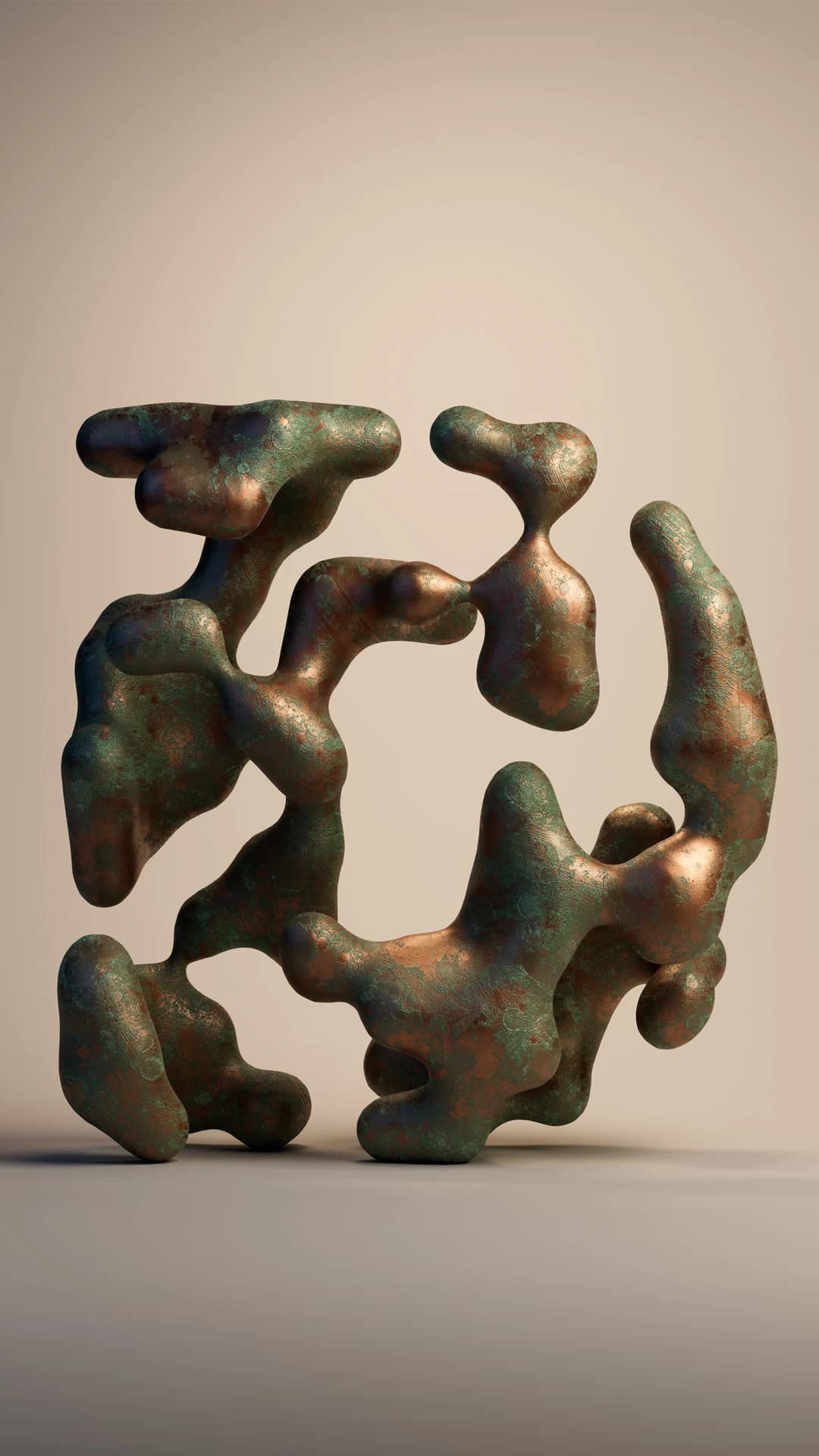
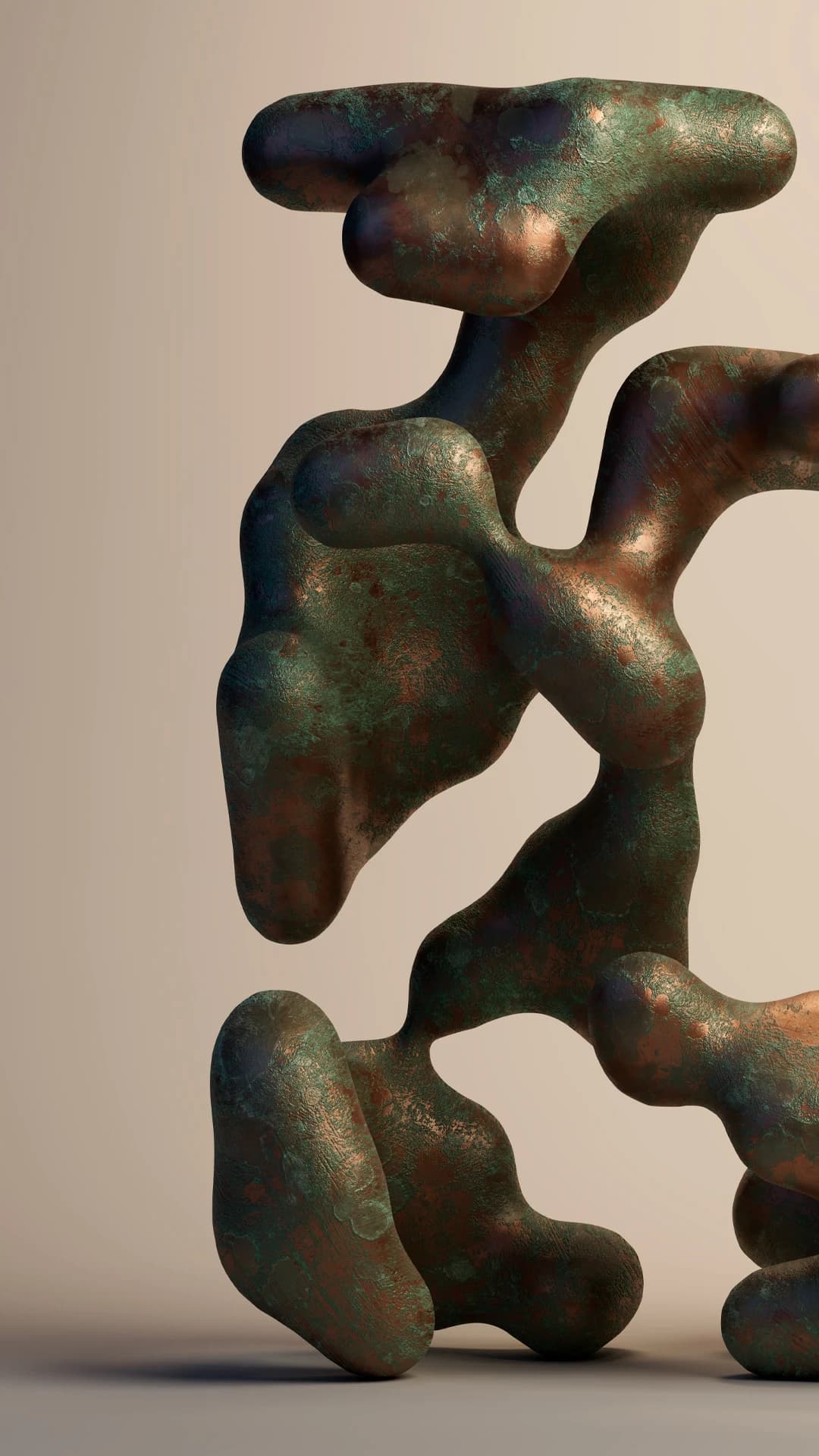
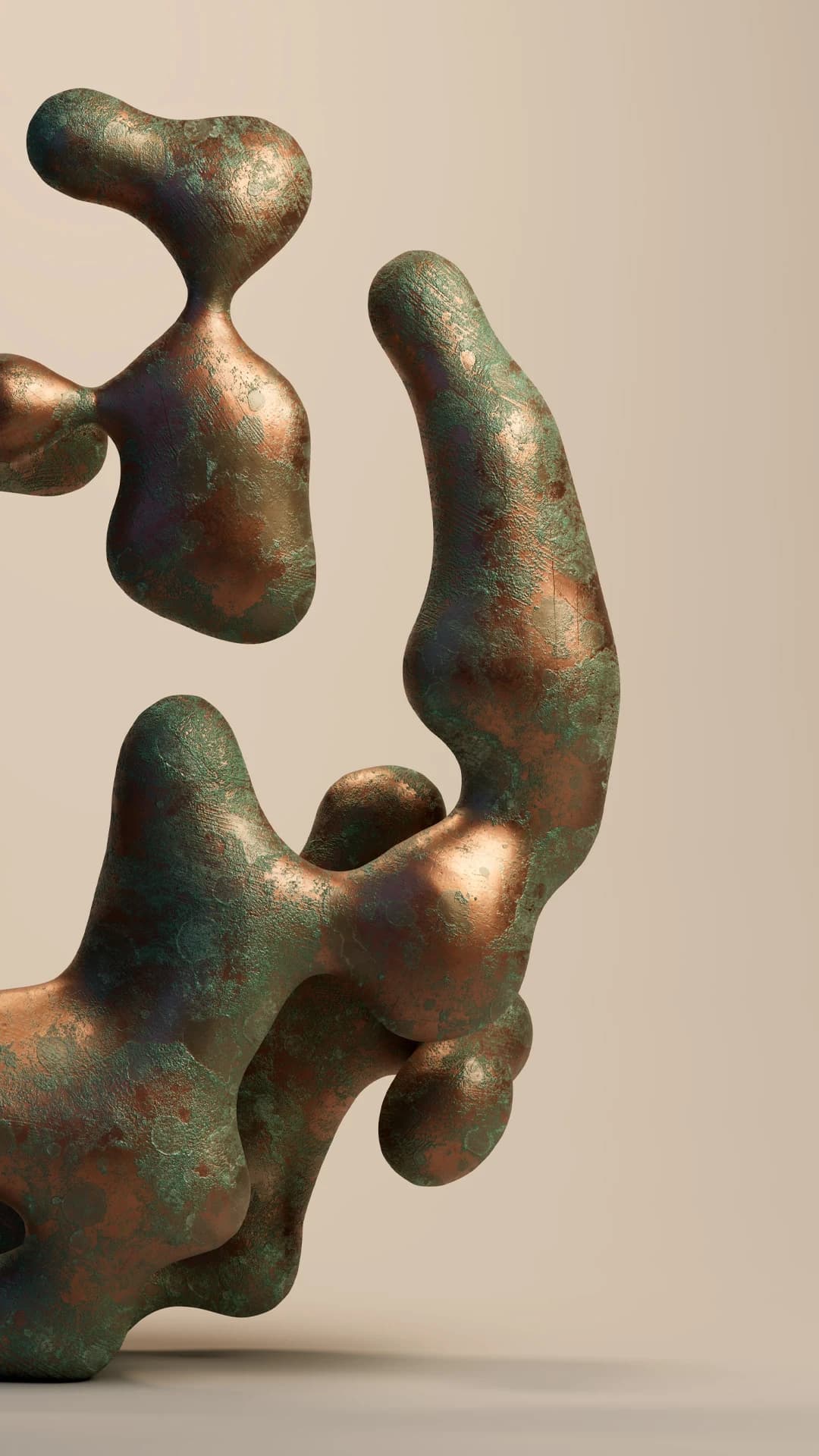
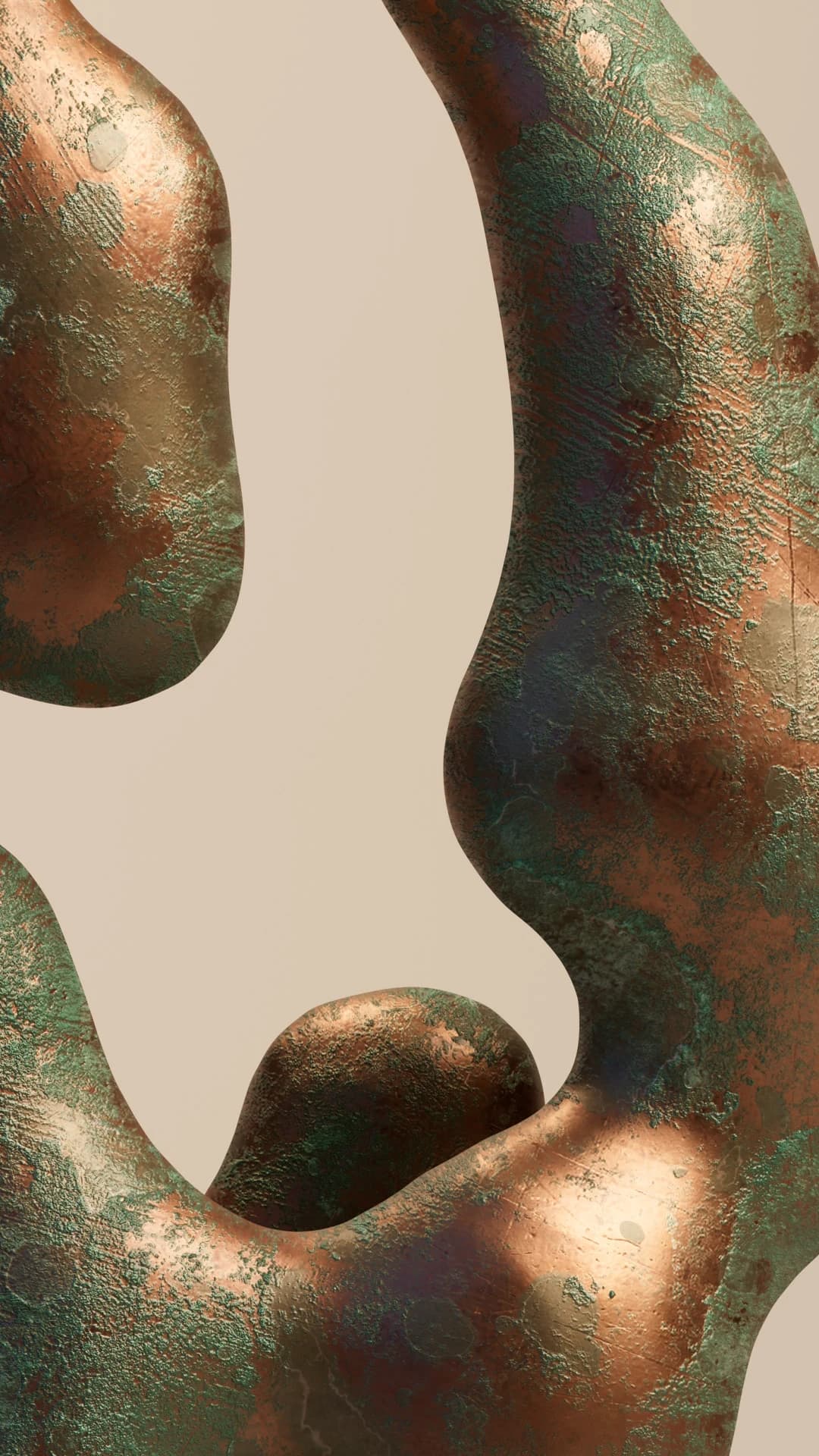
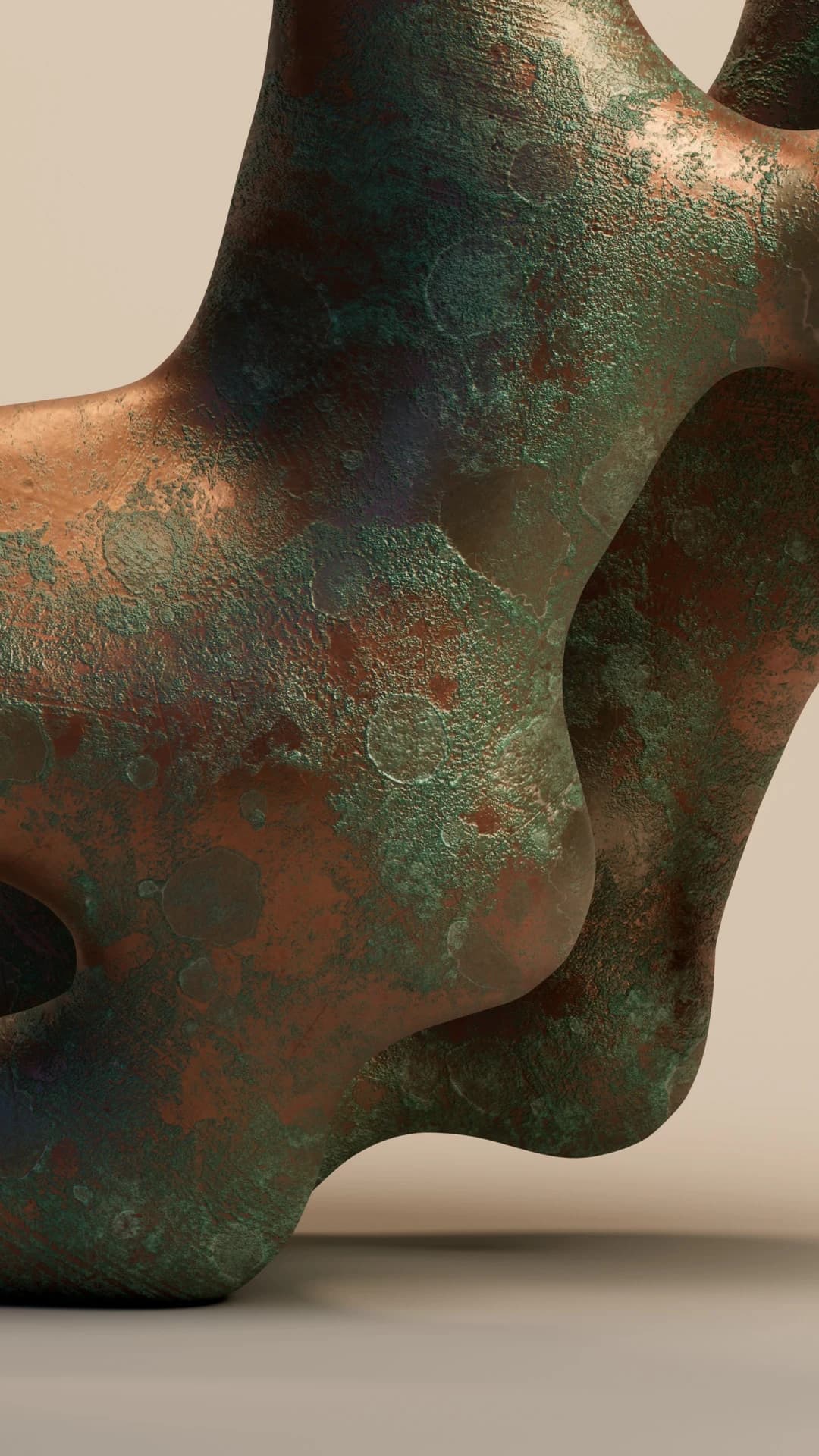
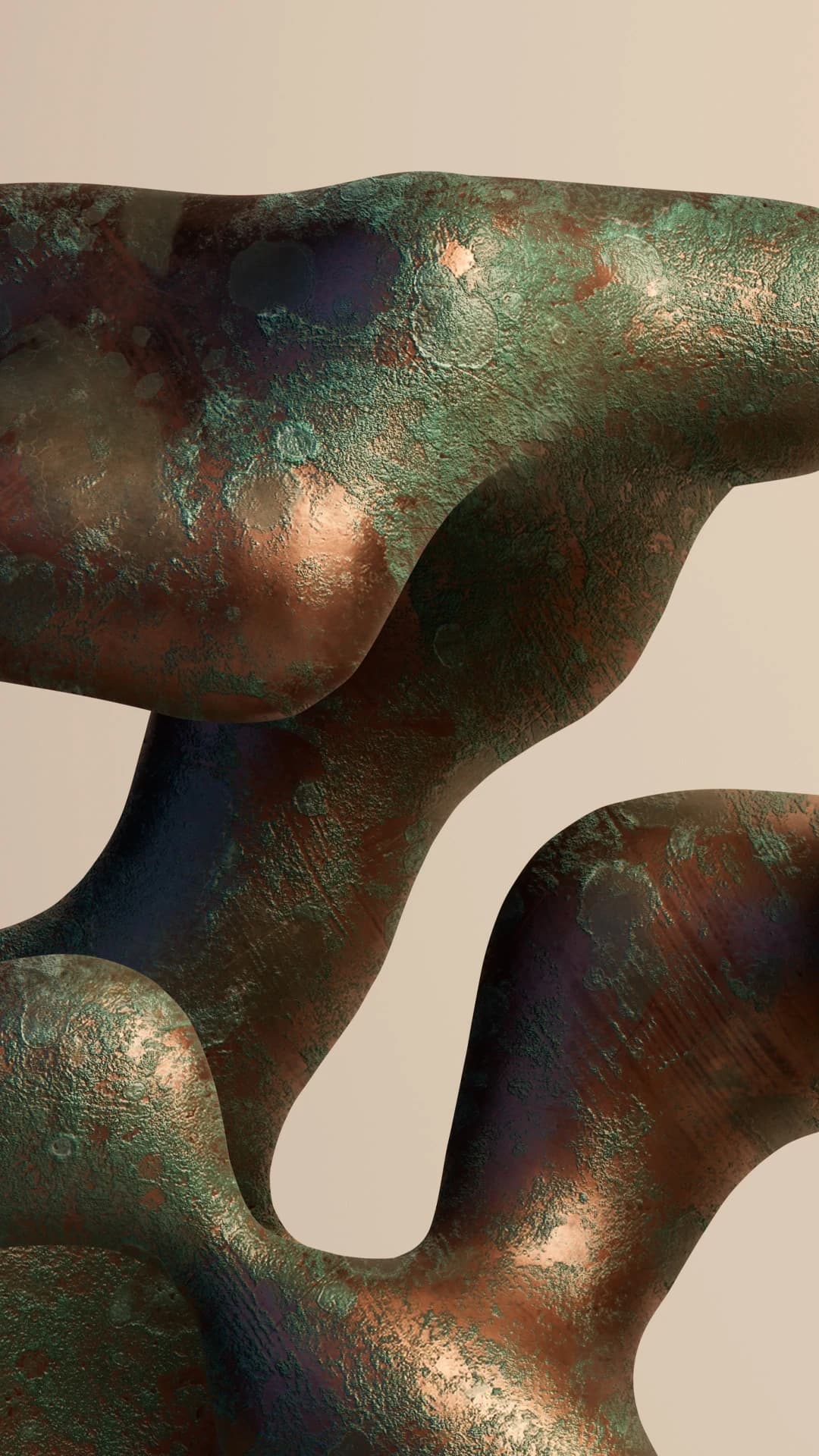
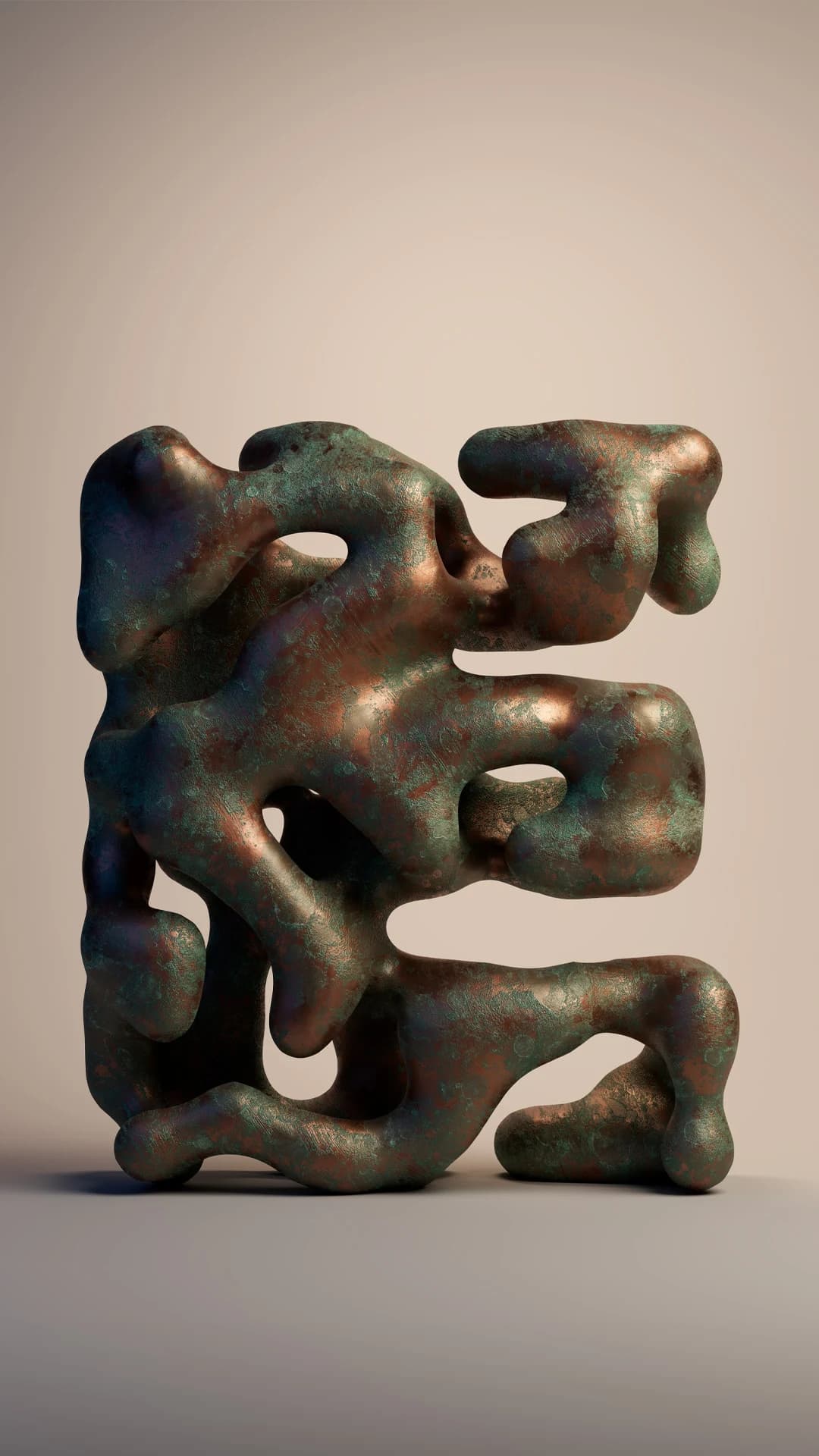
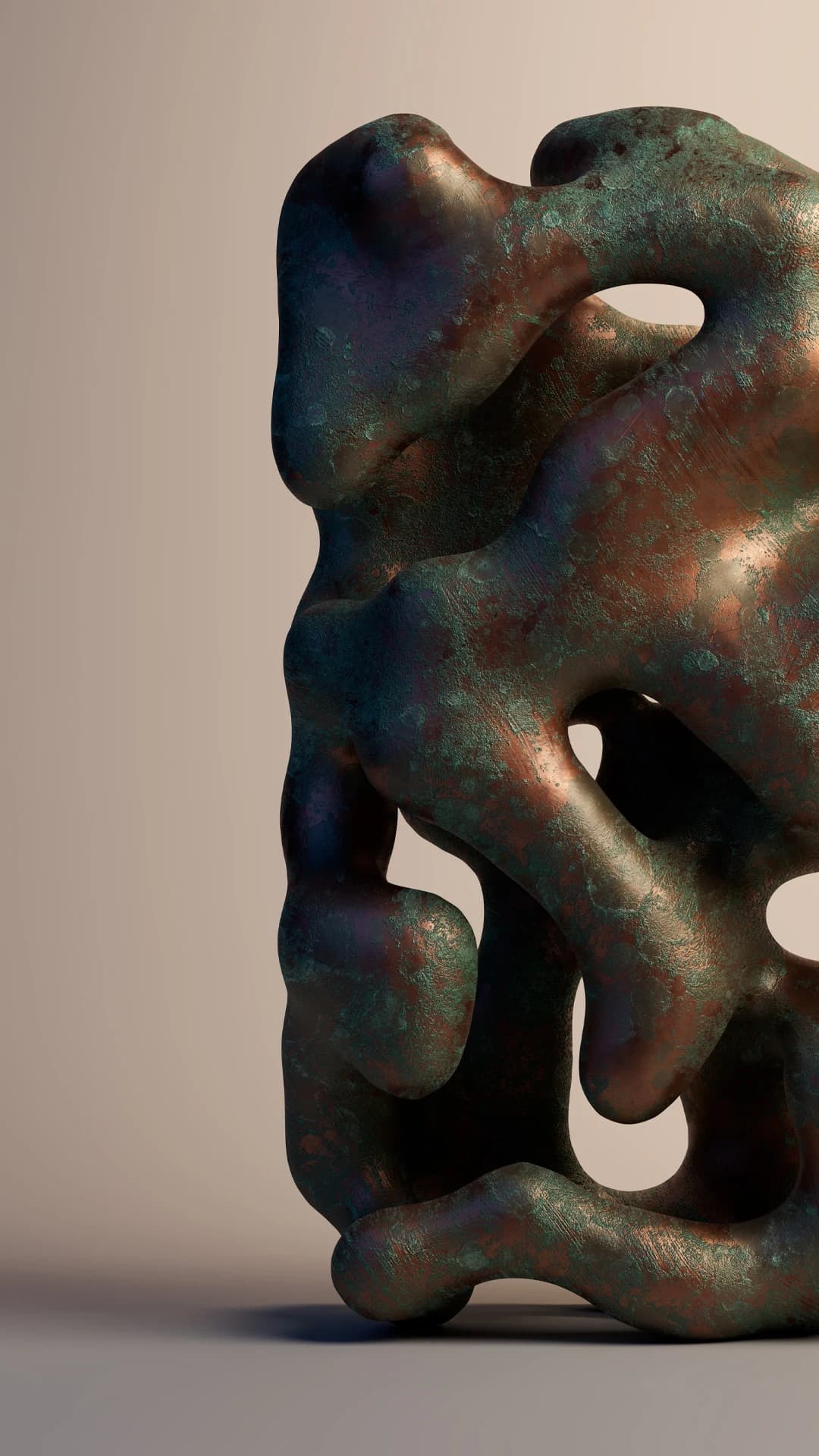
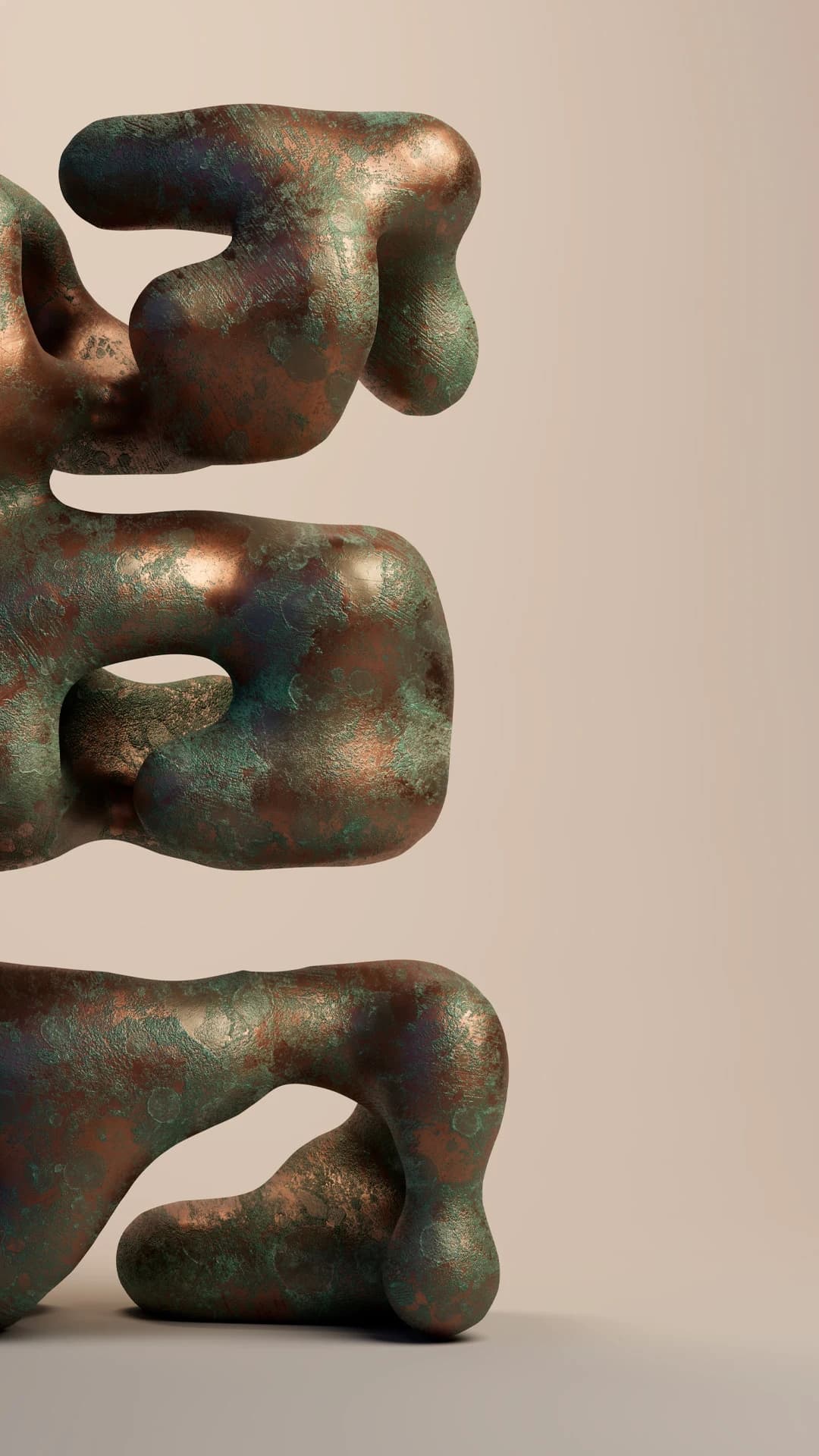
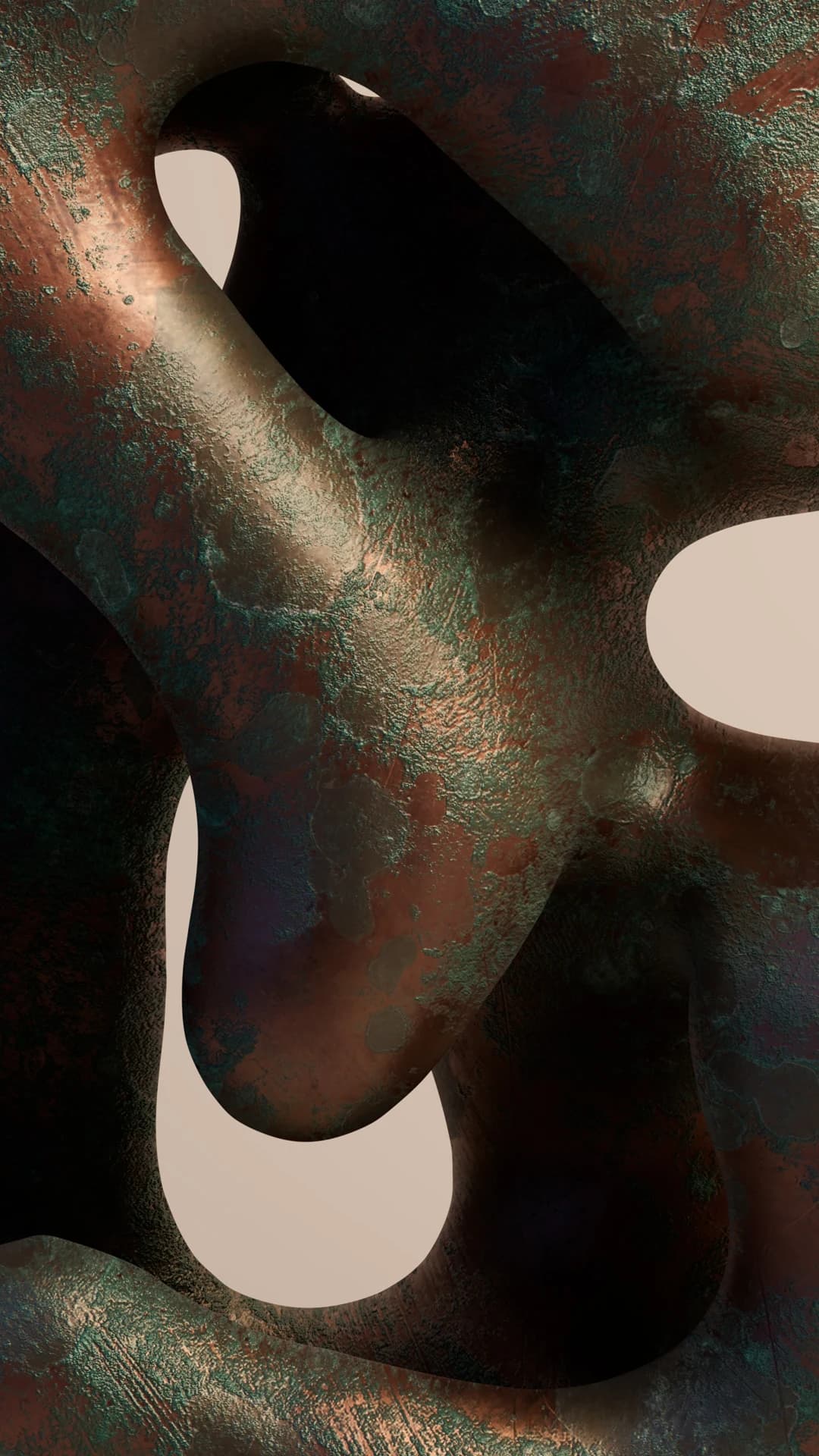
Los tipos metálicos imponen restricciones formales concretas: grosor mínimo de trazos, tolerancias de fundición, geometría de contrapunzones. La forma tipográfica se negocia con esas restricciones. Este ejercicio opera sin ellas — parte de una forma libre y le asigna un material, observando cómo las propiedades de la simulación (peso aparente, oxidación, reflectancia) condicionan la percepción del objeto.
Cada letra se construye por fusión de módulos esféricos de radio variable. La pátina verdigrís se distribuye de forma procedural siguiendo la lógica geométrica del objeto: mayor concentración en concavidades, mínima en superficies convexas iluminadas.
Modelado biomorfo por fusión de esferas → asignación de material bronce PBR → ajuste procedural de distribución de pátina según geometría → iluminación lateral de estudio → selección de encuadres por letra.
12 renders de alta resolución, formato vertical.